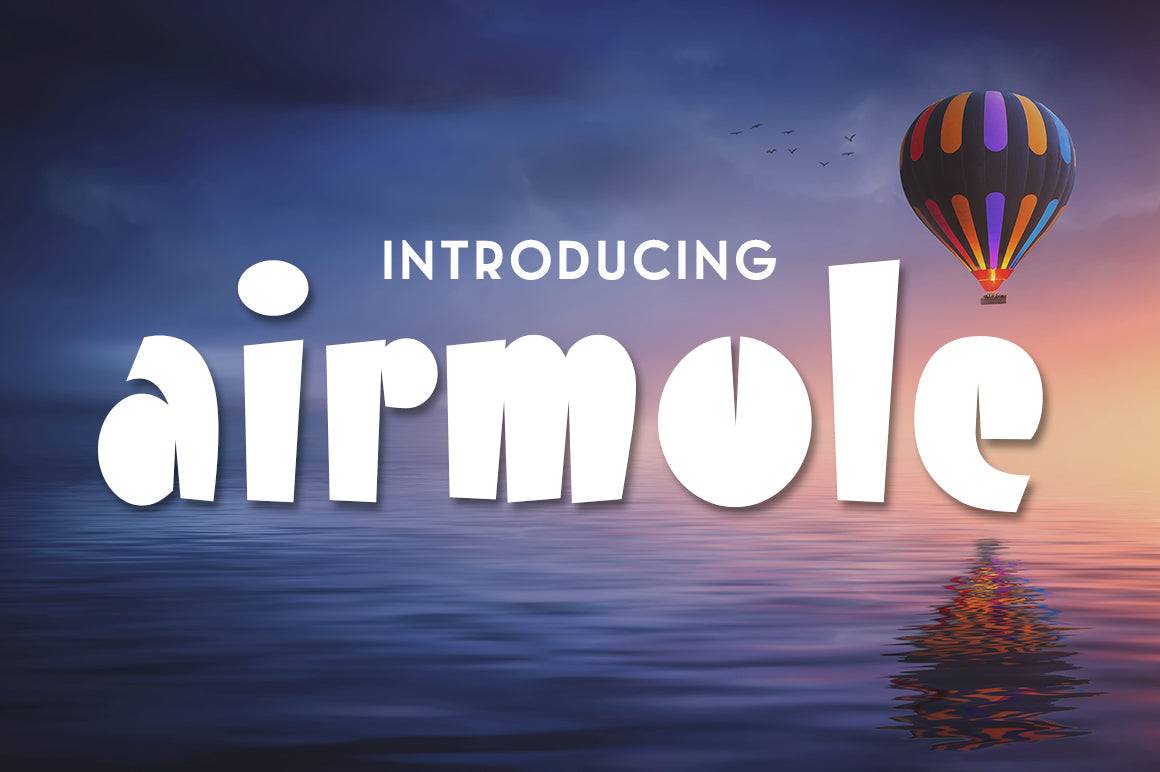
Fuente Airmole para Cricut, Silhouette y diseños imprimibles
Esta elegante fuente de estilo retro es ideal para usar con máquina de corte y para diseños imprimibles. Airmole presenta bordes suaves y formas geométricas, lo que la hace muy legible y visualmente atractiva para todo tipo de manualidades.
Como fuente, Airmole funciona a la perfección en proyectos de diseño tanto personales como empresariales, ofreciendo un rendimiento consistente en formatos impresos, cortados y digitales. Es ideal para todo tipo de proyectos, desde decoración en vinilo hasta productos de marca.
Su simplicidad, facilidad de uso y versatilidad lo convierten en una solución ideal tanto para aficionados al bricolaje como para diseñadores profesionales.
Lo que puedes hacer
- Calcomanías, etiquetas y plantillas de vinilo
- Invitaciones, tarjetas y señalización imprimibles
- Camisetas, tazas y vasos personalizados
- Elementos del logotipo y embalaje del producto
- Citas, arte mural y materiales para el aula.
Por qué te encantará
- Atractivo retro-moderno con legibilidad fluida.
- Excelente para proyectos de corte e impresión.
- Gran equilibrio entre carácter y utilidad.
P: ¿Qué tipo de fuente es Airmole?
A: Airmole es una fuente de visualización redondeada con un toque retro, optimizada para máquinas de corte y diseños imprimibles.
P: ¿La fuente es buena para vinilo e impresión?
R: Por supuesto. Sus curvas suaves y su diseño audaz lo hacen ideal para vinilo, materiales imprimibles y productos promocionales.
| Característica | Fuente Airmole | Fuente redondeada A | Sans Serif básica B |
| Estilo de fuente | Exhibición retro redondeada | Letras estilo burbuja | Sans-serif neutral |
| Casos de uso | Corte, etiquetas, merchandising | Manualidades y decoración para niños | Web e informes |